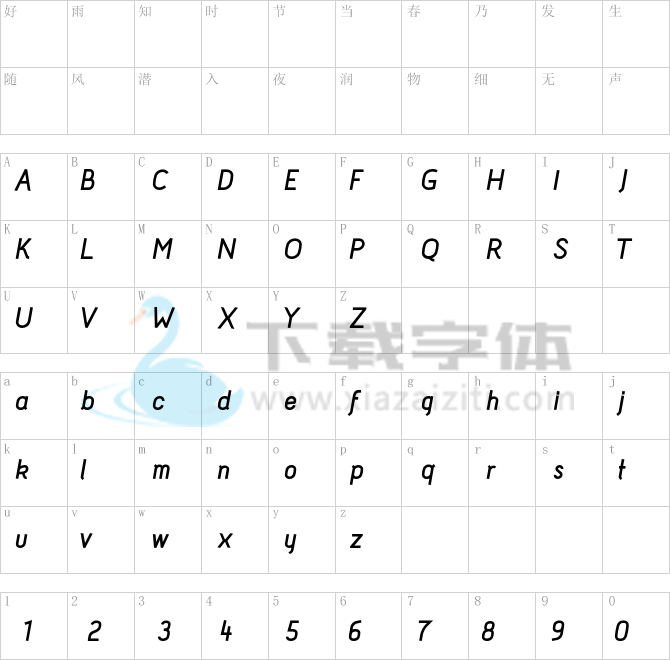
Acid.otf字体下载,这款字体结构工整、笔画清晰,兼顾美观与易读性,适用于标题、正文、海报、包装、LOGO 等多种场景。字形优雅稳定,风格百搭耐看,适配日常排版与创意设计,让文字呈现更舒适、更具质感。Acid.otf字体下载一笔一画,皆是细节,以均衡的比例、流畅的线条打造舒适视觉体验,字形端正大气,风格简约现代。无论是商业设计、品牌宣传还是日常排版,都能轻松驾驭,让文字更有格调与力量。Acid.otf字体下载字体下载。